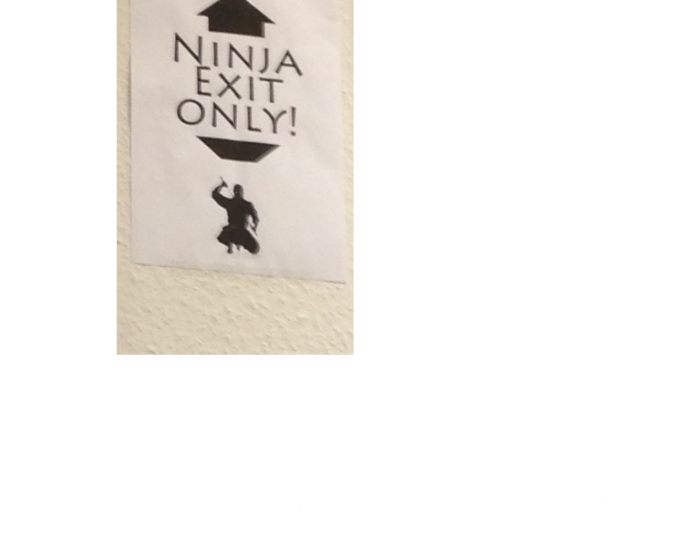
Welche Schriftart ist das?
Bild ist leider nicht ganz scharf. Auf einschlägigen Suchsites habe ich bereits versucht etwas passendes zu finden aber leider ohne Erfolg. Wobei das J und Y ja recht speziell sind.
Glaube sie gefunden zu haben.
"Lithos" kann das jemand bestätigen?